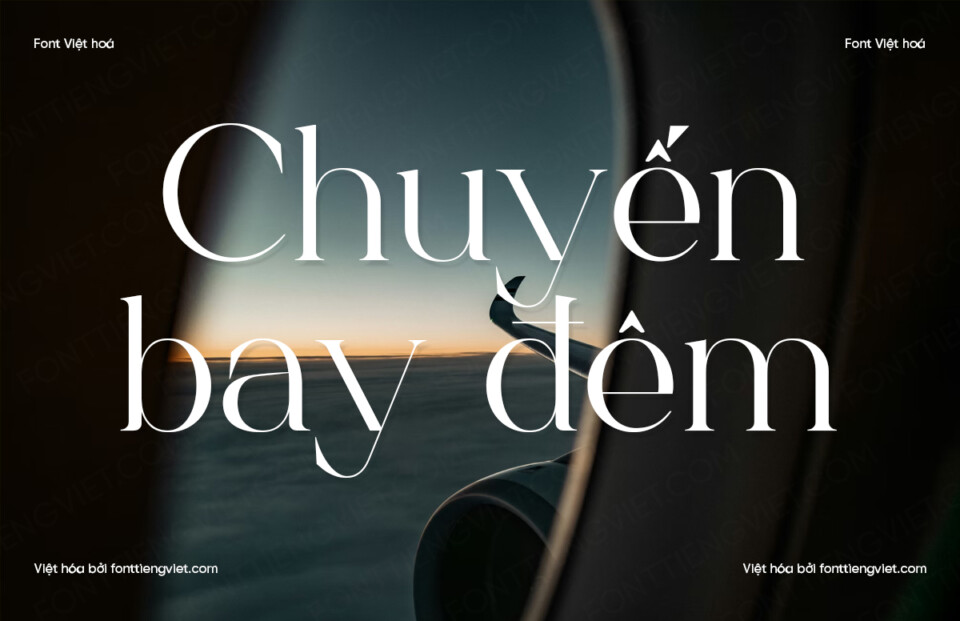
Tải Ngay Font Việt hóa 1FTV VIP Eclleria Sang Trọng Cho Thiết KếGiới thiệu bộ Font Việt hóa 1FTV VIP Eclleria đẳng cấpTrong thế giới thiết kế đồ họa, việc lựa chọn một Font Miễn Phí chất lượng luôn là ưu tiên hàng đầu của các bạn học sinh và thầy cô giáo khi làm slide bài giảng hay thiết kế báo tường. Bộ Font Việt hóa 1FTV VIP Eclleria nổi bật như một giải pháp hoàn hảo, mang đến vẻ đẹp thanh lịch, hiện đại và vô cùng chuyên nghiệp cho mọi tác phẩm nghệ thuật chữ.Đặc điểm nổi bật của kiểu chữ EclleriaBộ chữ này sở hữu các đường nét thanh mảnh kết hợp tinh tế với những nét uốn lượn mềm mại. Nhờ được tối ưu hóa hoàn toàn cho bảng mã tiếng Việt, người dùng không còn lo lắng về lỗi font hay mất dấu khi gõ văn bản, giúp quá trình sáng tạo trở nên mượt mà hơn bao giờ hết.Ứng dụng Font Việt hóa 1FTV VIP Eclleria trong giáo dục và đời sốngThiết kế này cực kỳ phù hợp để làm tiêu đề cho các slide thuyết trình môn Ngữ văn, Lịch sử hoặc các buổi lễ hội tại nhà trường. Sự trang trọng của font chữ giúp bài học trở nên lôi cuốn, thu hút sự chú ý của học sinh và tạo ấn tượng mạnh mẽ với người xem.Cách kết hợp font chữ hiệu quảĐể đạt hiệu quả thẩm mỹ cao nhất, bạn nên sử dụng kiểu chữ này cho các phần tựa đề lớn, kết hợp cùng các font chữ không chân đơn giản ở phần nội dung để tạo sự cân bằng và dễ đọc.Tải bộ chữ độc đáo này ở đâu?Nếu bạn đang tìm kiếm một công cụ để nâng tầm phong cách thiết kế của mình, hãy truy cập ngay kho tài nguyên Font Miễn Phí, Font Việt Hóa, Font Việt hóa 1FTV VIP Eclleria để tải về hoàn toàn miễn phí. Đây chắc chắn là người bạn đồng hành không thể thiếu cho các dự án sáng tạo sắp tới của bạn.
Font Việt hóa 1FTV VIP Eclleria